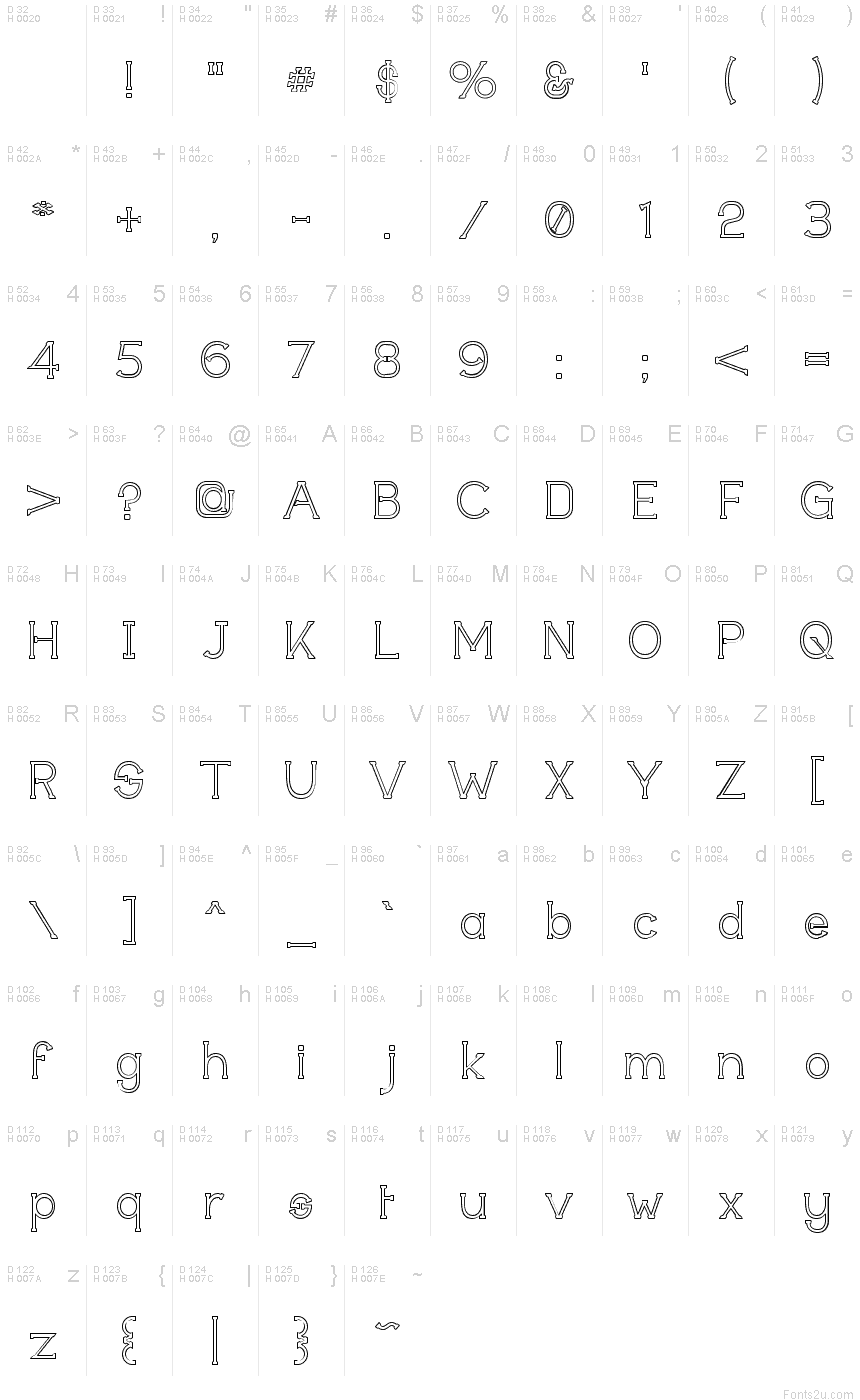
Technically Insane Outline
Technically Insane Outline od GemFonts98 to darmowy, konturowy font typu display w stylu techno, niosący w sobie dziwny, retro-futurystyczny spokój. Litery łączą szerokie proporcje – niemal jak w szyldach – z wyraźnymi podwójnymi liniami, kwadratowymi zakończeniami przypominającymi szeryfy i kilkoma wygięciami przypominającymi obwody, co nadaje krojowi technicznego, choć nieco nietypowego charakteru.
Znajdzie naturalne zastosowanie na ulotkach arcade, okładkach zinów, tytułach sci-fi, plakatach i szkicach logotypów, gdzie ten darmowy font doda struktury, nie sprawiając wrażenia chłodnego. Sprawdza się szczególnie w krótkich słowach, inicjałach i monogramach, ponieważ otwarty kontur i zdecydowane narożniki sprawiają, że litery są lekkie, a zarazem wyglądają na celowo zaprojektowane.